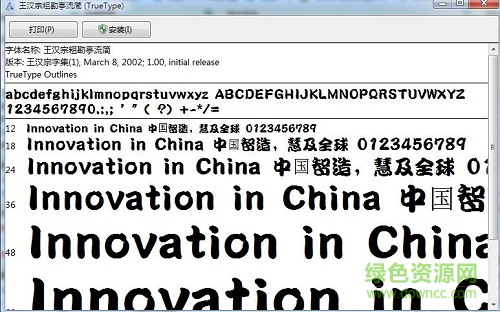
王漢宗粗勘亭流簡是王漢宗根據(jù)日本江戶時(shí)代的文字研發(fā)的一款中文字體,筆畫粗,字形圓潤、敦厚,非常適合用來做醒目的標(biāo)題使用,有需要?dú)g迎免費(fèi)下載!
王漢宗粗勘亭流簡是王漢宗打造的一款粗體勘亭字體,在繼承了勘亭流體基礎(chǔ)之上,對(duì)字體進(jìn)行了加粗,讓字形變得更加的大氣磅礴,變得更加的醒目,非常適合用于各種標(biāo)題!